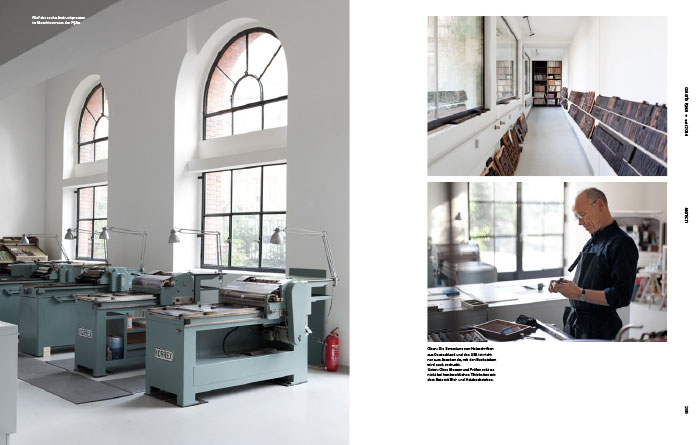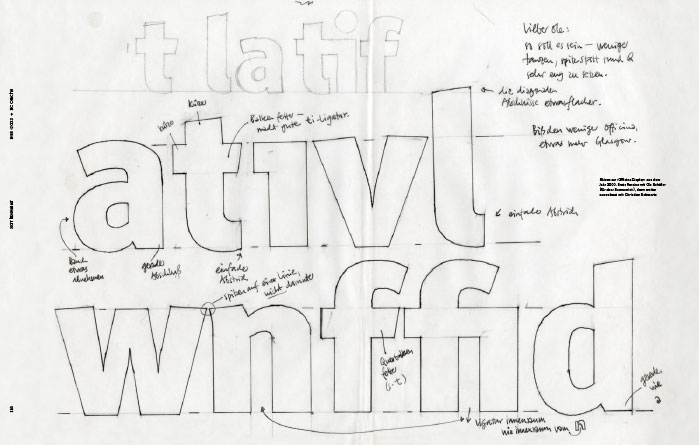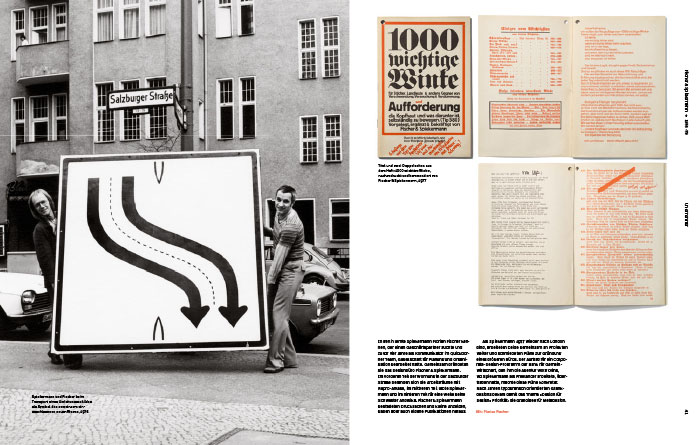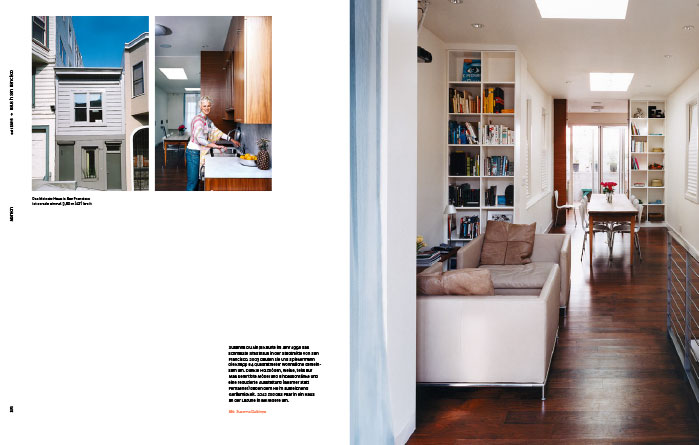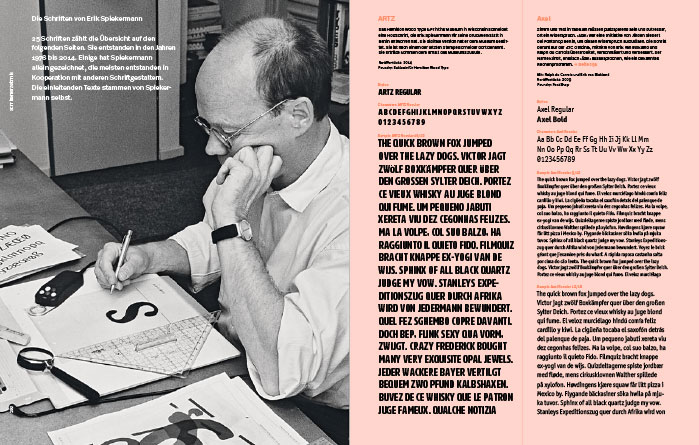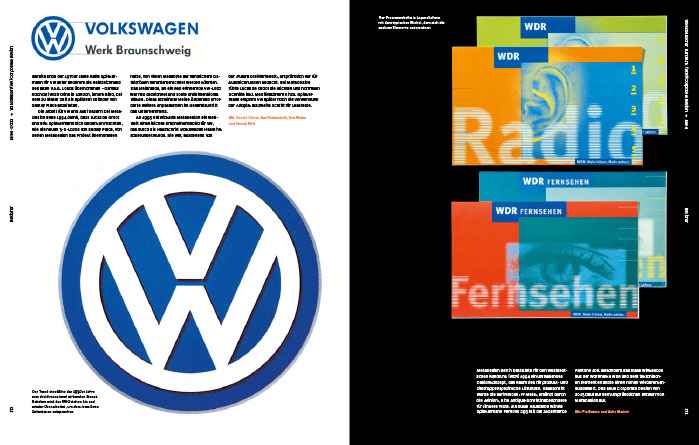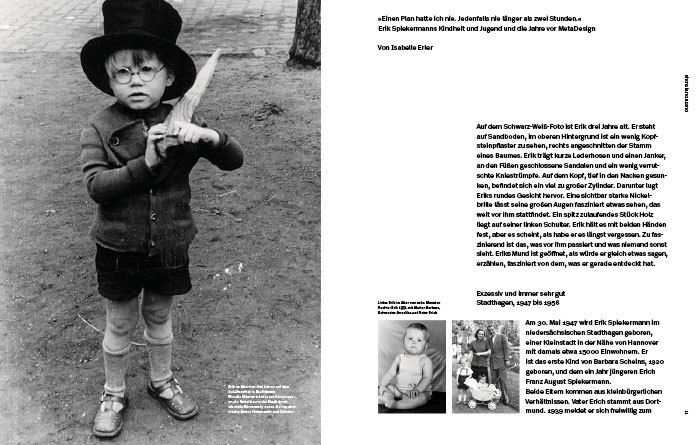
Hallo, ich bin Erik
Erik Spiekermann ist der wohl bekannteste deutschsprachige Typograf. Nach einem schaffensreichen Arbeitsleben zieht er sich nun gerade Schritt für Schritt aus dem Alltagsgeschäft zurück. Die von ihm maßgeblich mitbegründete gelb-schwarze Schriftenwelt der FontFont-Bibliothek und des FontShop-Versandhandels trat er kürzlich zur Überraschung vieler an Monotype ab. Dafür kehrt Erik nun wieder zu seinem Wurzeln als Drucker zurück und ist häufig in seiner neuen Hochdruck-Werkstatt p98a zu finden. Es ist ein passender Zeitpunkt, um auf sein Lebenswerk zurückzublicken. Sein Weggefährte Johannes Erler hat dazu in Zusammenarbeit mit dem Verlag »Gestalten« die Biografie »Hallo, ich bin Erik« erarbeitet. Doch kann sie uns noch viel Neues verraten, dass wir nicht ohnehin schon über den omnipräsenten »Typomanen« Spiekermann wissen? Ich finde, durchaus!
Das Buch ist keine klassische Biografie in Gestalt eines durchgängigen Fließtextes, sondern eher fragmentarisch angelegt. In voneinander unabhängigen Texten und Interviews berichten Erler und viele Weggefährten über Abschnitte von Spiekermanns beruflichem und privatem Leben sowie den konkreten Projekten und zahlreichen Unternehmungen. Dies macht das Werk erfreulich abwechslungsreich und kurzweilig. Die Anektdoten von Kollegen und die reiche Bebilderung aus Privatfotos und unzähligen Arbeitsproben trägt ihr Übriges dazu bei.
Gesetzt ist das 320-seitige, in Deutschland gedruckte Hardcover-Buch in einem extra angefertigten, halbfetten Schnitt der Akzidenz-Grotesk, den Käufer des Buches mit einem persönlichen Code auch herunterladen können. Das großzügige Format und die Gestaltung sind der Aufmachung als Portfolio-Präsentation angepasst. Die Texte sind aber dementsprechend oft recht klein gesetzt. Die beißend-orange Leuchtfarbe kommt zum Glück nur ab und zu als Hintergrund und für kurze Textabschnitte zur Anwendung.
Lediglich Spiekermanns Schriftentwürfe sind in einem gesonderten Teil am Ende des Buches zusammengefasst. Ansonsten zieht sich die umfassende Werkschau (verteilt auf die sieben Abschnitte »der Designer«, »der Schriftgestalter«, »der Unternehmer«, »der Netzwerker«, »der Autor«, »der Techniker« und »der Mensch«) nahezu über das gesamte Buch. Die Verbindung dieser Bereiche in einer Person ist es wohl auch, die Spiekermanns Wirken so besonders und erfolgreich macht. Und so feiert dieses Buch nicht nur das Lebenswerk Spiekermanns, sondern letztlich auch ganz allgemein die Rolle erfolgreichen Kommunikationsdesigns – als ein Werkzeug der Verständigung, das, ob es den Menschen bewusst ist oder nicht, nahezu alle Teile unseres Lebens berührt. »Es ging mir immer und bis heute darum, Kommunikation möglichst präzise zu gestalten. Ich möchte verständlich sein, weil ich finde, dass es unendlich viel zu entdecken und zu verstehen gibt. Das wollte ich mein ganzes Leben lang«. (Erik Spiekermann)
Untertitel: Erik Spiekermann, Schriftgestalter, Designer, Unternehmer
Autor(en): Johannes Erler